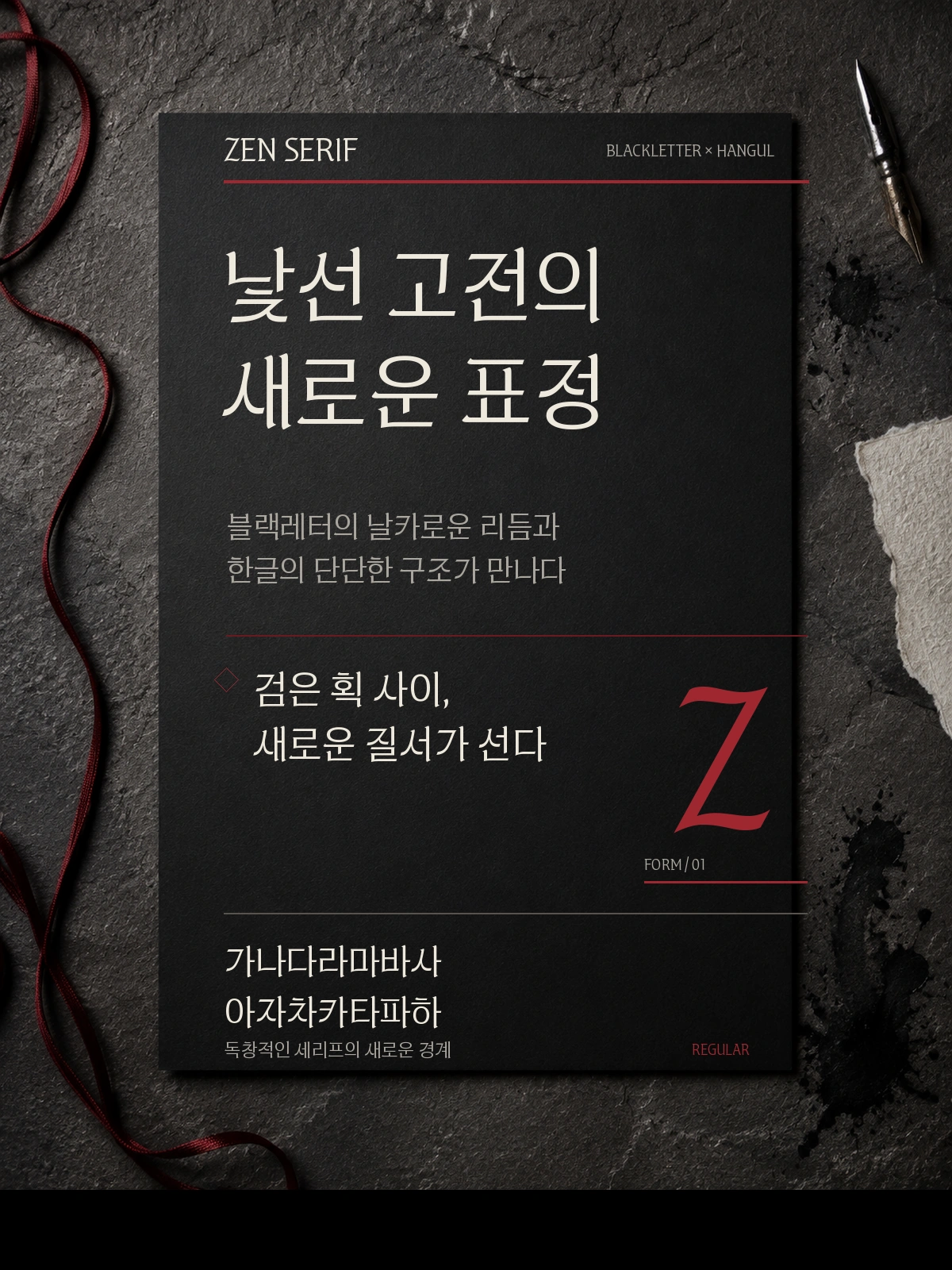
ZEN SERIF — OA엔터테인먼에서 배포하는 무료 폰트입니다. 블랙레터의 강한 인상을 한글 세리프 구조에 끌어들인, 독창적인 제목용 세리프 서체
OA엔터테인먼트가 2025년 10월에 공개한 세리프 서체입니다. 공지 페이지에는 이름과 다운로드 링크뿐이라 제작 의도나 이름의 유래는 알 수 없지만, 폰트 파일을 열어 보면 실제 제작은 이도타입이 맡았다는 사실이 나옵니다. 브랜드가 의뢰하고 전문 폰트 회사가 그린 구조입니다.
제작사가 남긴 조형 설명이 없어 형태는 파일에서 직접 재어 봤습니다. 세로획이 가로획의 1.8배로 부리 계열의 성격이 분명하고, 받침 유무에 따라 높이가 거의 변하지 않는 네모틀에 폭보다 높이가 큰 낱자를 씁니다. 현대 한글 11,172자를 모두 담아 어떤 음절이든 빠지지 않습니다. 굵기는 하나뿐입니다.